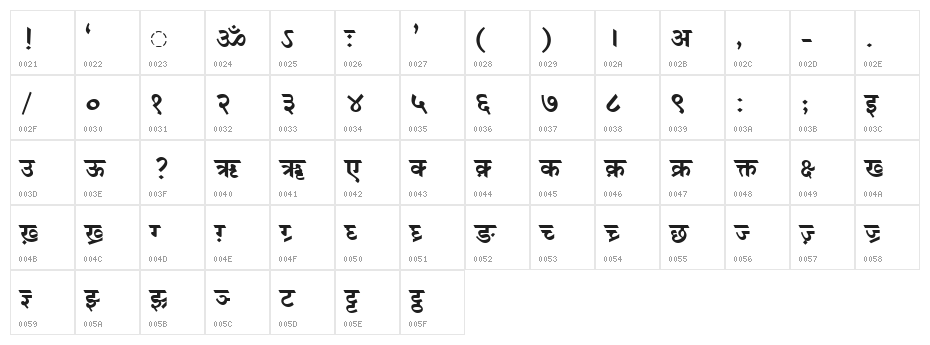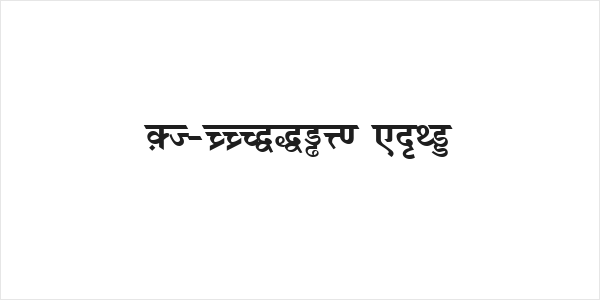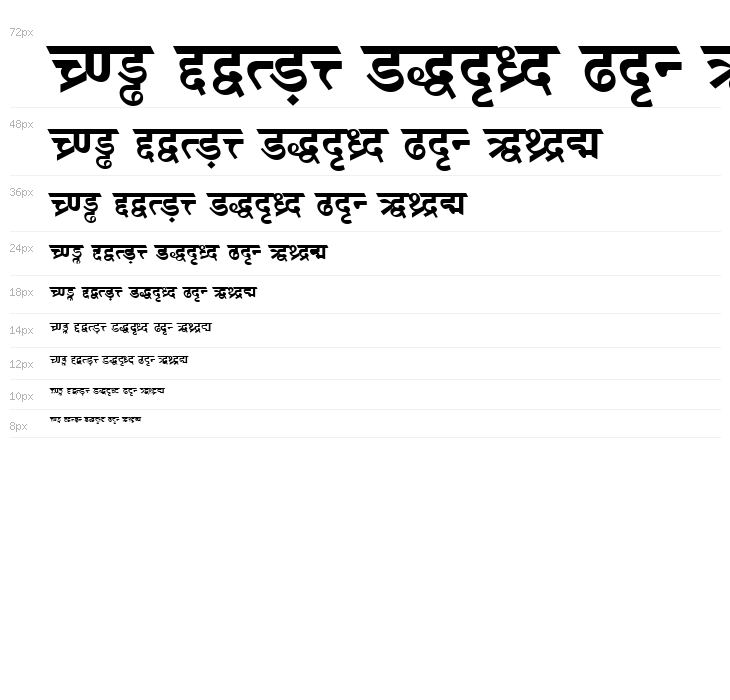
DV-TTSurekh Bold Font
| Caz de utilizare | Headlines, Signage, Posters |
| Proiecte propuse | Ideal for headlines, signage, posters, and any project requiring a bold Devanagari script. |